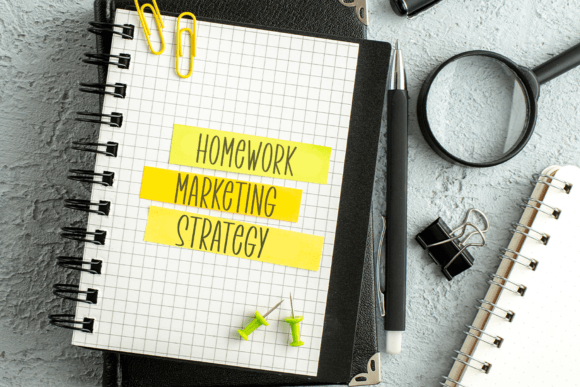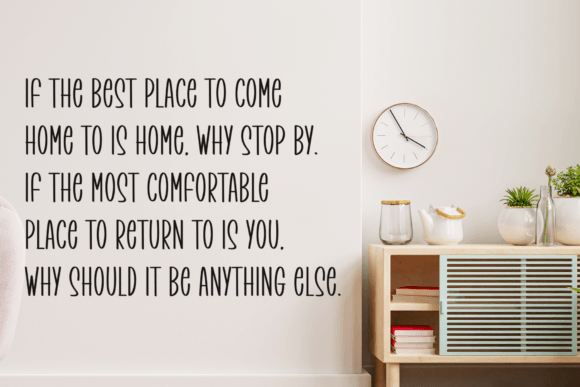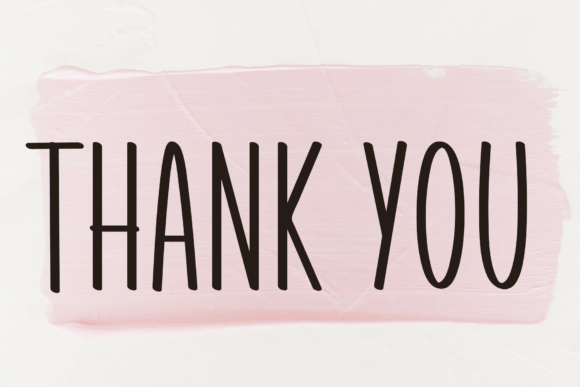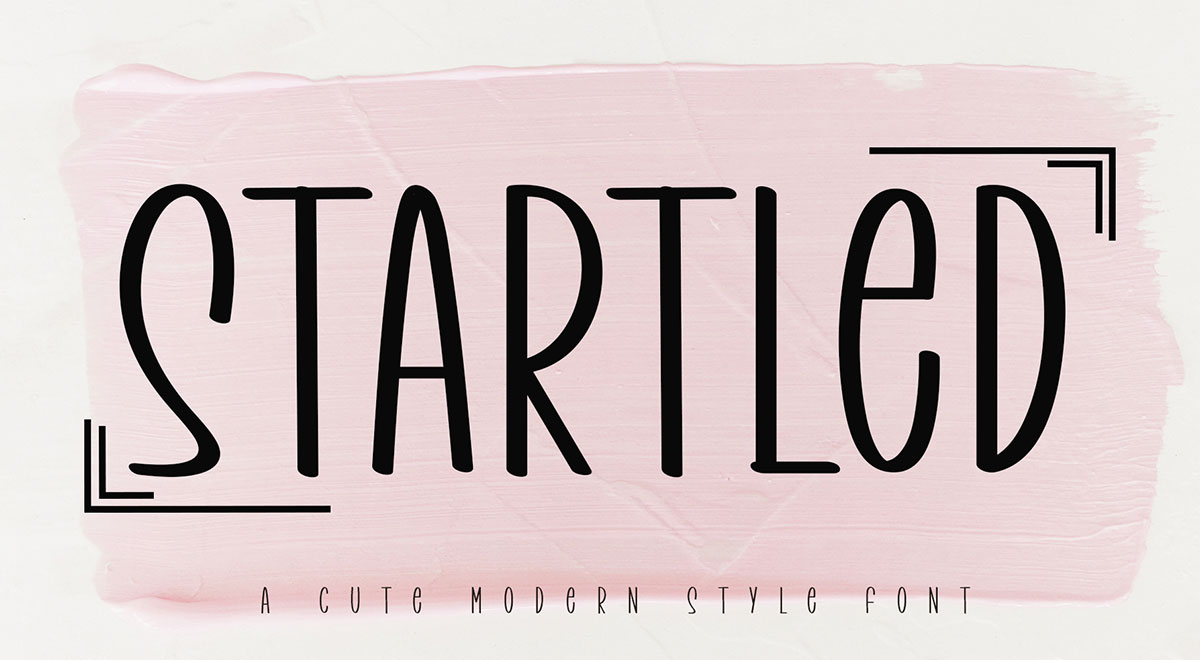
فونت Startled انگلیسی
دانلود فونت Startled انگلیسی Font استارتلد |
| ⭐ مجموعه فونت | دانلود فونت انگلیسی مبهوت Font Startled |
| ⭐ توضیحات | فونت Startled را معرفی می کنیم، یک فونت sans serif جسور و چشم نواز که با طراحی منحصر به فرد خود جلب توجه می کند. این فونت با خطوط تیز و حس معاصر خود، حسی از مدرنیته و جذابیت را به طراحی های شما می بخشد.
فونت Startled که برای تیترها، پوسترها و مواد برندسازی ایده آل است، نگاه بیننده را جلب می کند و حس هیجان را ایجاد می کند و متن شما را با حضور جسورانه و سبک مطمئن خود متمایز می کند. |